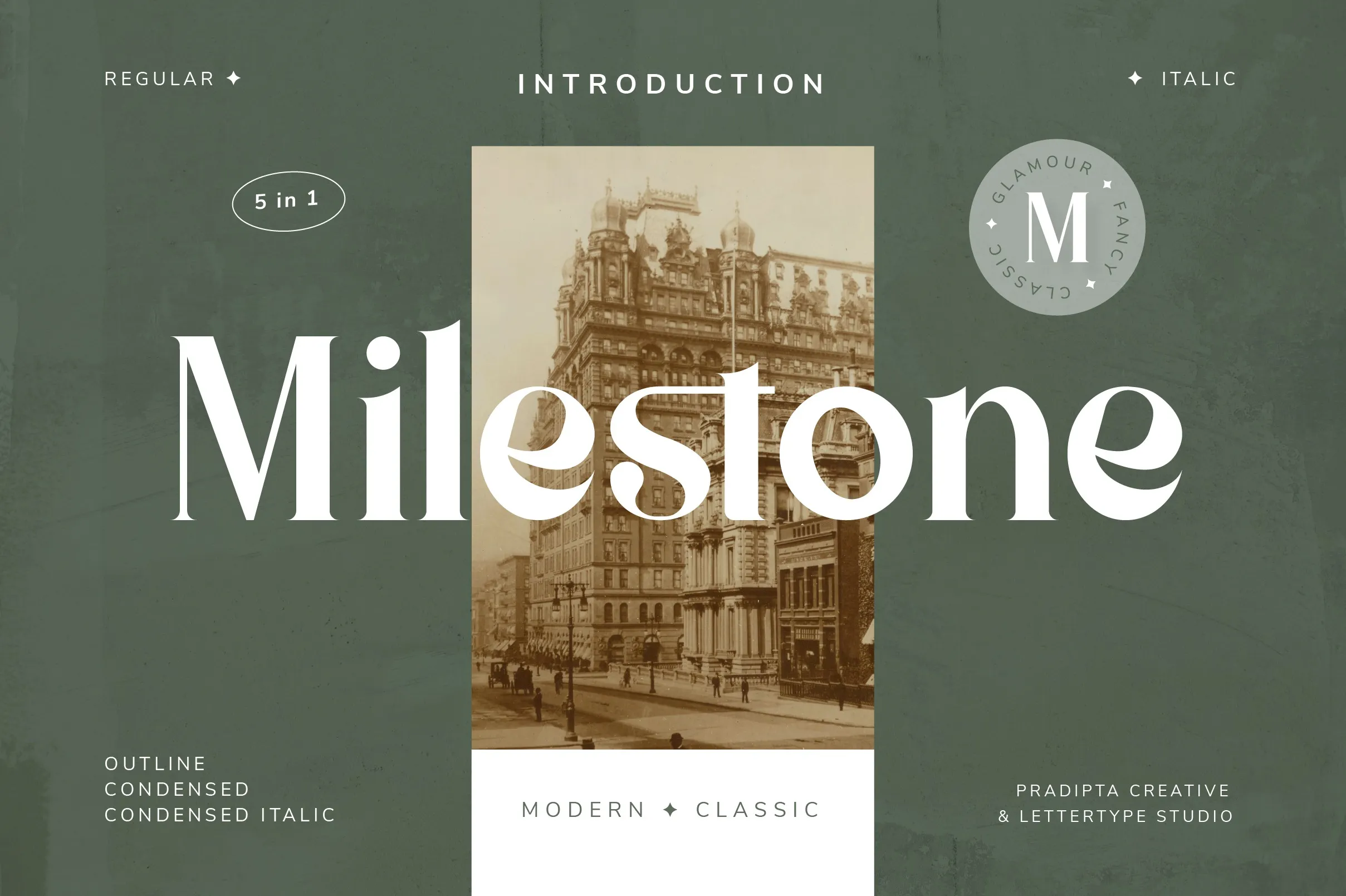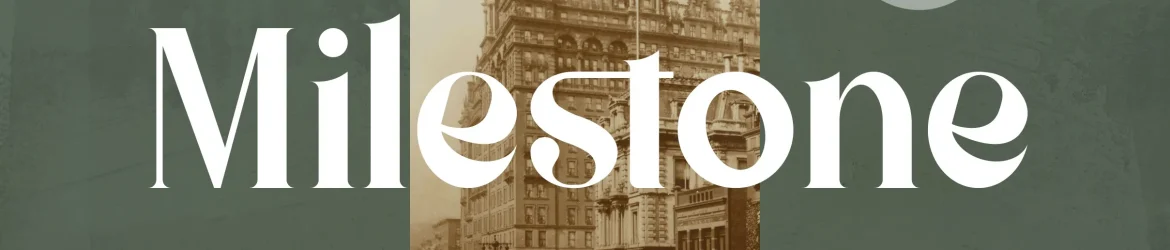
A Milestone Font é uma combinação perfeita entre a elegância tradicional dos caracteres serifados e o modernismo contemporâneo que traz seu projeto para um nível mais sofisticado e sofisticado. Este design de tipo elegante está repleto de estilo clássico, tornando-o ideal tanto para desenhos de logotipo quanto para criações de marca, roupas, sinalização, cabeçalhos em sites ou revistas, convites de casamento e muito mais. Com seu design sofisticado, a Milestone Font é uma escolha perfeita para quem busca dar um toque especial à sua identidade visual ou publicação. Experimente a Milestone Font para adicionar autenticidade ao seu trabalho gráfico.